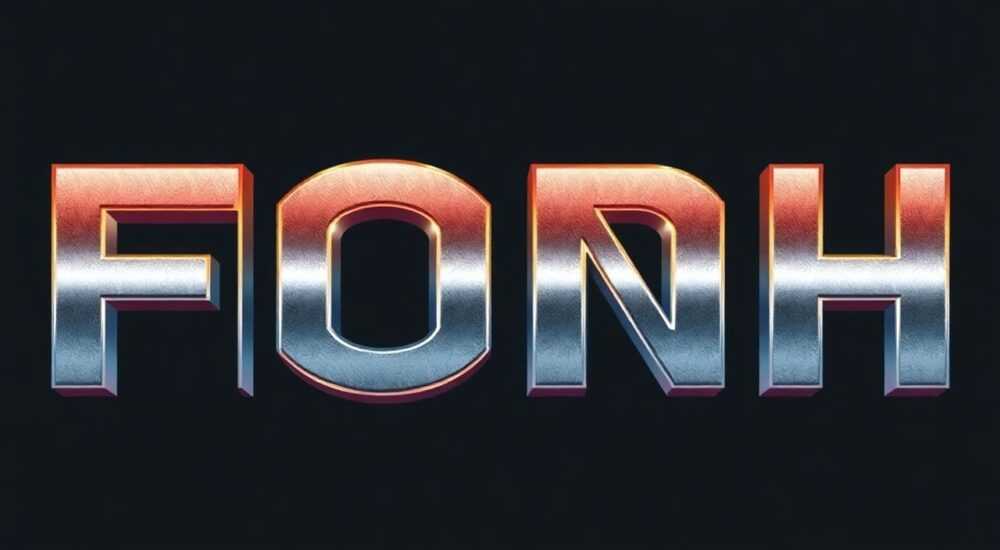
Как сделать металлический шрифт в фотошопе
Когда речь заходит о создании эффектных дизайнов — от логотипов до постеров и упаковки — металлический шрифт остаётся одним из самых востребованных стилей. Он передаёт премиальность, надёжность и современность, будь то в брендинге косметики, техники или ювелирных изделий. Однако многие пользователи Photoshop сталкиваются с трудностями: текст выглядит плоско, блёклый, неестественный или слишком «пластиковый». На самом деле, создание реалистичного металлического шрифта — это не просто применение наложения стиля, а комплексная работа с текстурой, светом, тенями и отражениями. С правильным подходом вы сможете воссоздать эффект полированной стали, бронзы, золота или хрома, который не отличить от настоящего металла.
Чтобы сделать металлический шрифт в Photoshop, используйте комбинацию стилей слоя: градиентную заливку с холодными и тёплыми оттенками, внутреннее свечение для бликов, внешнее свечение для контура, скос и эффект искры. Ключ — в тонкой настройке освещения и добавлении текстуры металлической поверхности через режим наложения.
Почему металлический шрифт так популярен в дизайне
Металлические шрифты — это не просто модный тренд, а мощный визуальный инструмент психологического воздействия. Исследования в области нейродизайна показывают, что металлические текстуры активируют у зрителя ассоциации с качеством, надёжностью и премиальностью. По данным Statista, в 2024 году более 68% брендов высокого сегмента (от косметики до электроники) использовали металлические акценты в логотипах и рекламных материалах. Это не случайно: металл воспринимается как символ долговечности, технологичности и роскоши.
Представьте, что вы смотрите на логотип бренда часов: один вариант — матовый чёрный текст, другой — с лёгким золотистым бликом и тонкими отражениями. Какой вызывает доверие? Второй. Даже если потребитель не может объяснить почему — он чувствует разницу. Именно поэтому дизайнеры стремятся не просто «сделать текст блестящим», а создать объём, глубину и реалистичную игру света.
Эффект металла особенно важен в таких нишах, как ювелирные изделия, автомобильная индустрия, премиальная упаковка и luxury-бренды. Но даже в более массовых сегментах — например, в рекламе спортивных товаров или гаджетов — металлический шрифт помогает выделиться среди конкурентов.
Полезно знать: Металлические текстуры лучше всего работают на тёмных или однотонных фонах. На сложных изображениях они теряют объём и могут выглядеть неестественно.
Пошаговое руководство: как сделать металлический шрифт в Photoshop
Создание реалистичного металлического шрифта требует системного подхода. Ниже — подробный алгоритм, который работает независимо от типа металла, который вы хотите имитировать.
1. Создайте текстовый слой. Выберите шрифт с чёткими формами — идеально подходят геометрические или модернистские типы: Montserrat Bold, Bebas Neue, Futura PT, или даже Trajan Pro для классического эффекта. Избегайте слишком тонких или декоративных шрифтов: они потеряют детализацию при наложении эффектов.
2. Увеличьте размер шрифта. Чем больше текст, тем детальнее вы сможете проработать блики и тени. Рекомендуемый минимум — 120 pt для печати, 200 pt для цифровых проектов.
3. Примените градиентную заливку. Откройте окно «Стиль слоя» → «Наложение градиента». Используйте двухцветный градиент: для хрома — #f0f0f0 → #666666, для золота — #ffd700 → #b8860b, для бронзы — #cd7f32 → #8b4513. Установите угол 90°, тип — линейный. Включите опцию «Прозрачность» и сдвиньте ползунок прозрачности влево до 20–30%, чтобы создать лёгкую «пятнистость».
4. Добавьте внутреннее свечение. В том же окне выберите «Внутреннее свечение». Цвет — белый или светло-серый. Размер — 3–5 пикселей, расстояние — 0, художественное сглаживание — включено. Это создаёт эффект внутреннего свечения, характерный для полированного металла.
5. Настройте скос и эффект. Выберите «Скос и эффект». Стиль — «Внешний скос», метод — «Гладкий», глубина — 100%, размер — 5–7 пикселей. Угол — 120°, высота — 30°. Цвет тени — тёмно-серый (#222222), цвет подсветки — белый или светло-жёлтый. Это придаст тексту объём и ощущение рельефа.
6. Добавьте внешнее свечение. Выберите «Внешнее свечение». Цвет — почти белый (#ffffff), размер — 1–2 пикселя, расстояние — 0. Это создаст тонкий контур, как у отполированного металла под ярким светом.
7. Наложите текстуру металла. Загрузите текстуру полированной стали или бронзы (можно найти на Unsplash или TextureKing). Поместите её поверх текста, измените режим наложения на «Перекрытие» или «Жёсткий свет» (5–15% непрозрачности). Примените маску слоя и стерите текст, чтобы текстура проявилась только внутри букв.
8. Используйте фильтр «Размытие по Гауссу». Скопируйте текстовый слой, преобразуйте его в смарт-объект, примените размытие по Гауссу на 0.5–1 пиксель. Уменьшите непрозрачность до 30–40%. Это смягчит резкие края и сделает металл более естественным.
Полезно знать: Всегда сохраняйте исходный текстовый слой отдельно. Это позволит в будущем легко менять текст без повторного наложения стилей.
Разные типы металлов: золото, хром, бронза, сталь
Металл — не единый материал. Каждый тип требует своей цветовой палитры, интенсивности бликов и степени отражения. Ниже — таблица, помогающая быстро подобрать параметры для разных металлов.